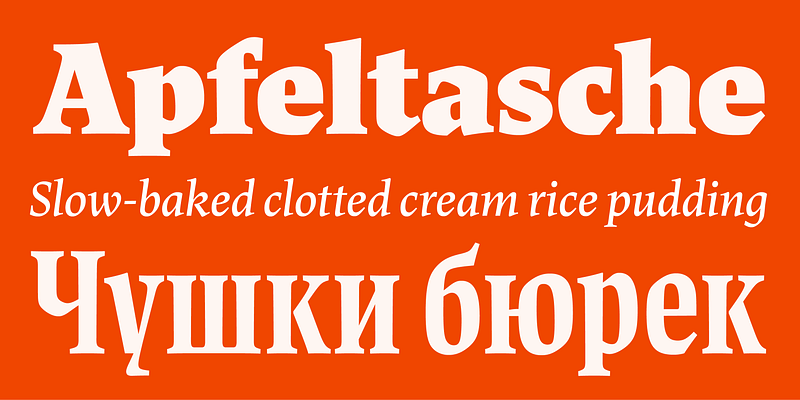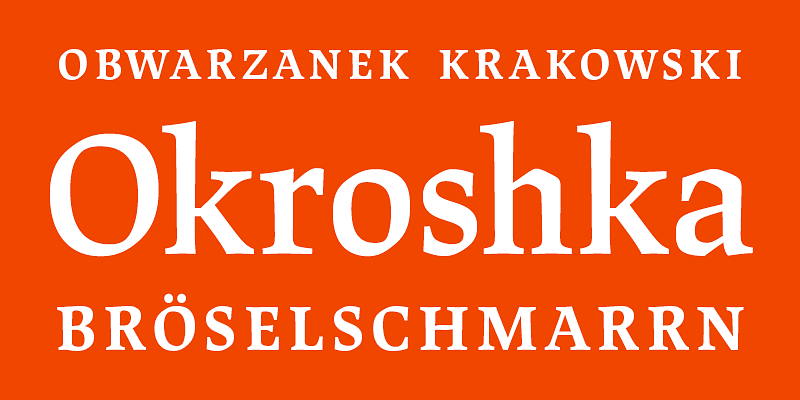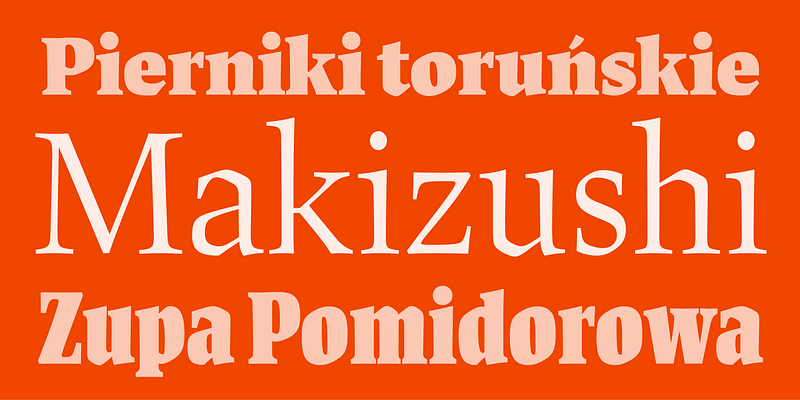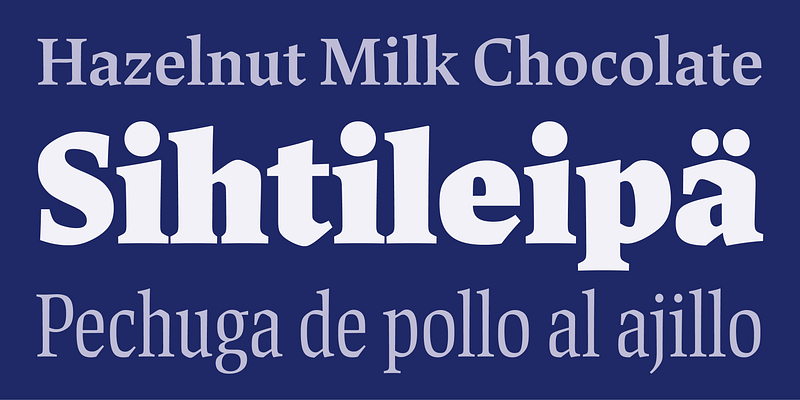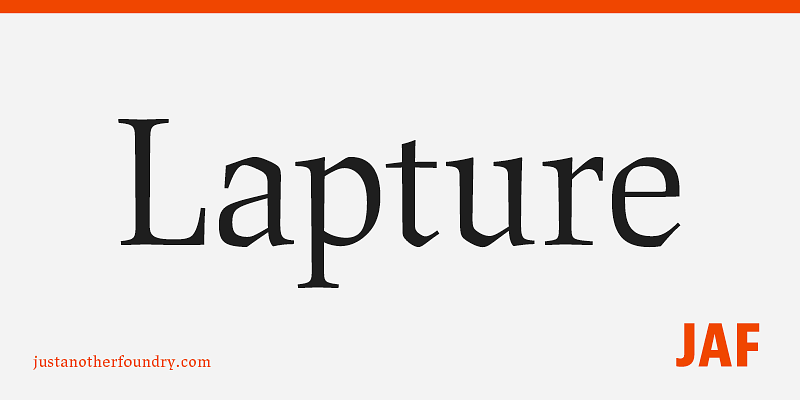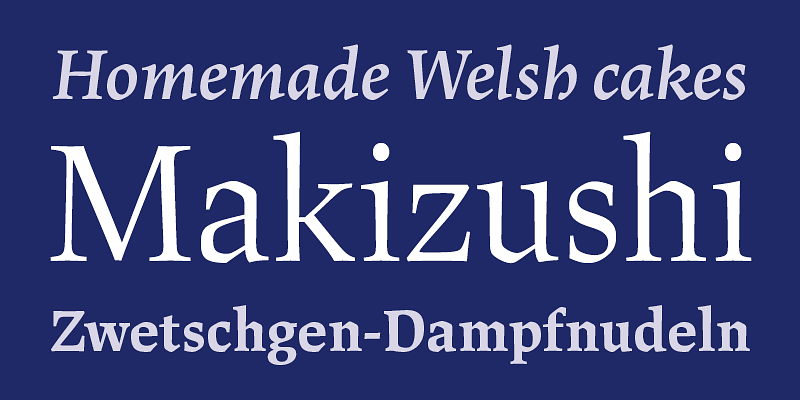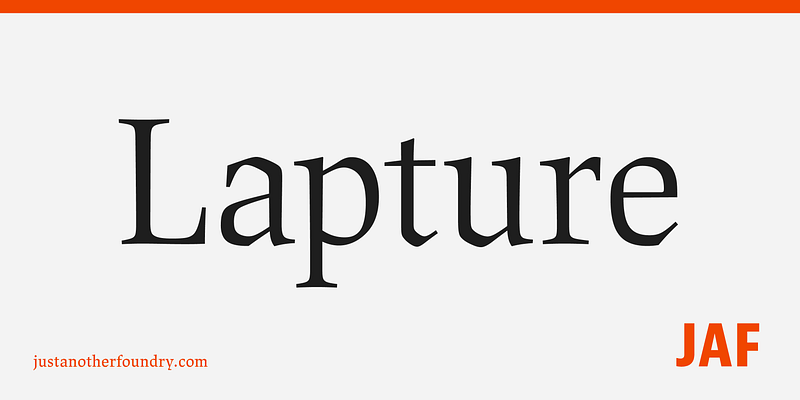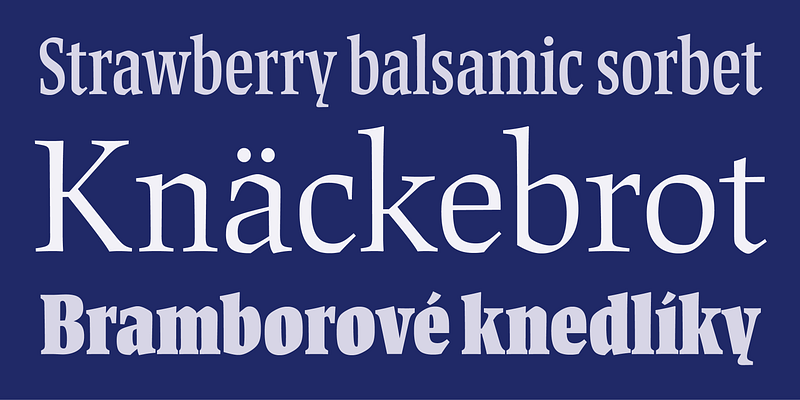
Just Another Foundry は書体デザイナーのティム・アーレンス氏とタイポグラファーの麥倉聖子氏によって運営されるドイツの書体デザイン事務所です。伝統を尊重しつつも新しくブラックレターを解釈した書体 JAF Lapture や JAF Herb(共に2011年ATypI letter.2賞受賞)、可視性と可読性に優れる万能のサンセリフ書体 JAF Bernini Sans(2013年NY TDC賞受賞)、コントラストを抑えた落ち着いた印象のラウンド・サンス JAF Domus など、多数の独自性のある優れた書体を生み出し続けています。クライアントの特別なニーズに合わせた書体開発も行っており、Crown Equipment Corporation や OECD(経済協力開発機構)のカスタム書体や、セイコーのコーポレート書体も手掛けています。